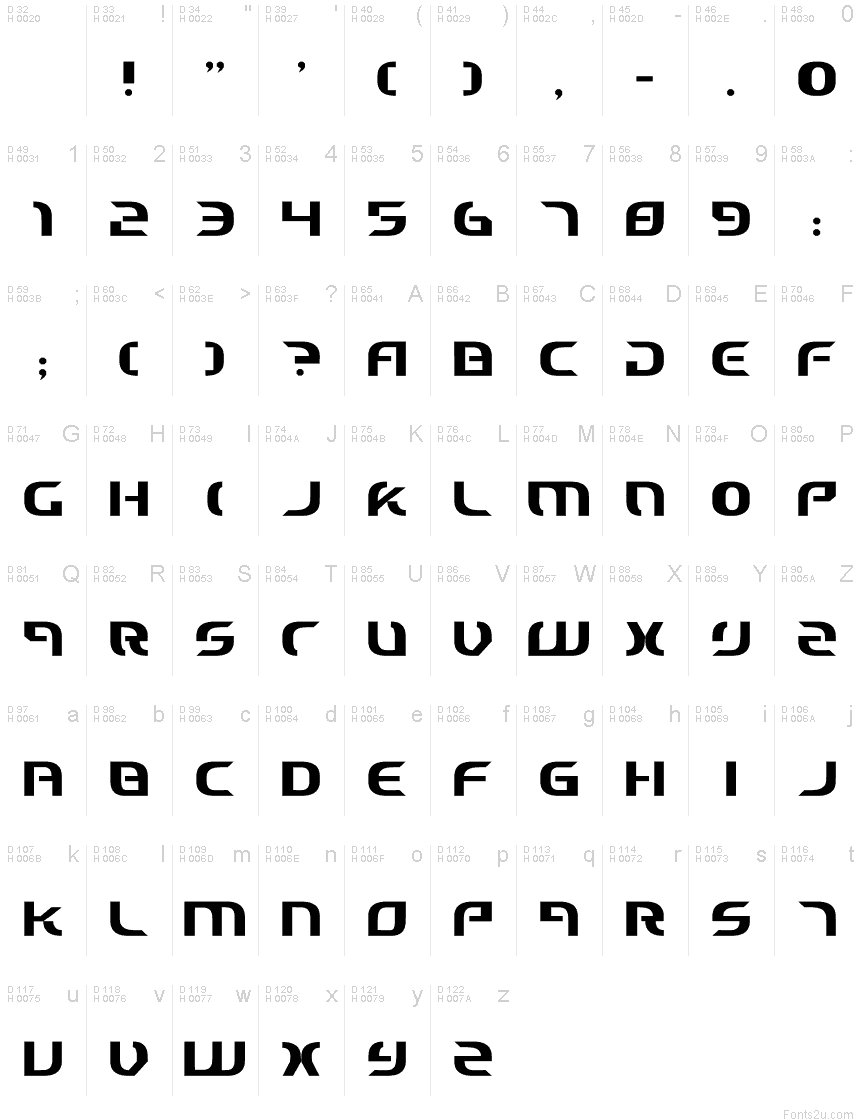
Starfighter Cadet od Iconian Fonts to darmowy, futurystyczny krój pisma typu display, pisany wielkimi literami, z eleganckim klimatem science-fiction późnych lat 90. Litery zbudowane są z szerokich, geometrycznych kresek i głęboko wyciętych łuków, dzięki czemu wyglądają bardziej jak oznaczenia na statku kosmicznym niż neutralny zestaw w stylu techno.
Świetnie sprawdzi się w logotypach gier, filmowych napisach, nagłówkach plakatów, okładkach muzyki elektronicznej czy monogramach, gdzie kilka liter musi nadawać ton. Jako darmowy font, najlepiej sprawdza się w krótkich formach graficznych, ponieważ rzeźbione łuki i masywne łączenia nadają nawet krótkim słowom mocny, syntetyczny, międzygwiezdny charakter.